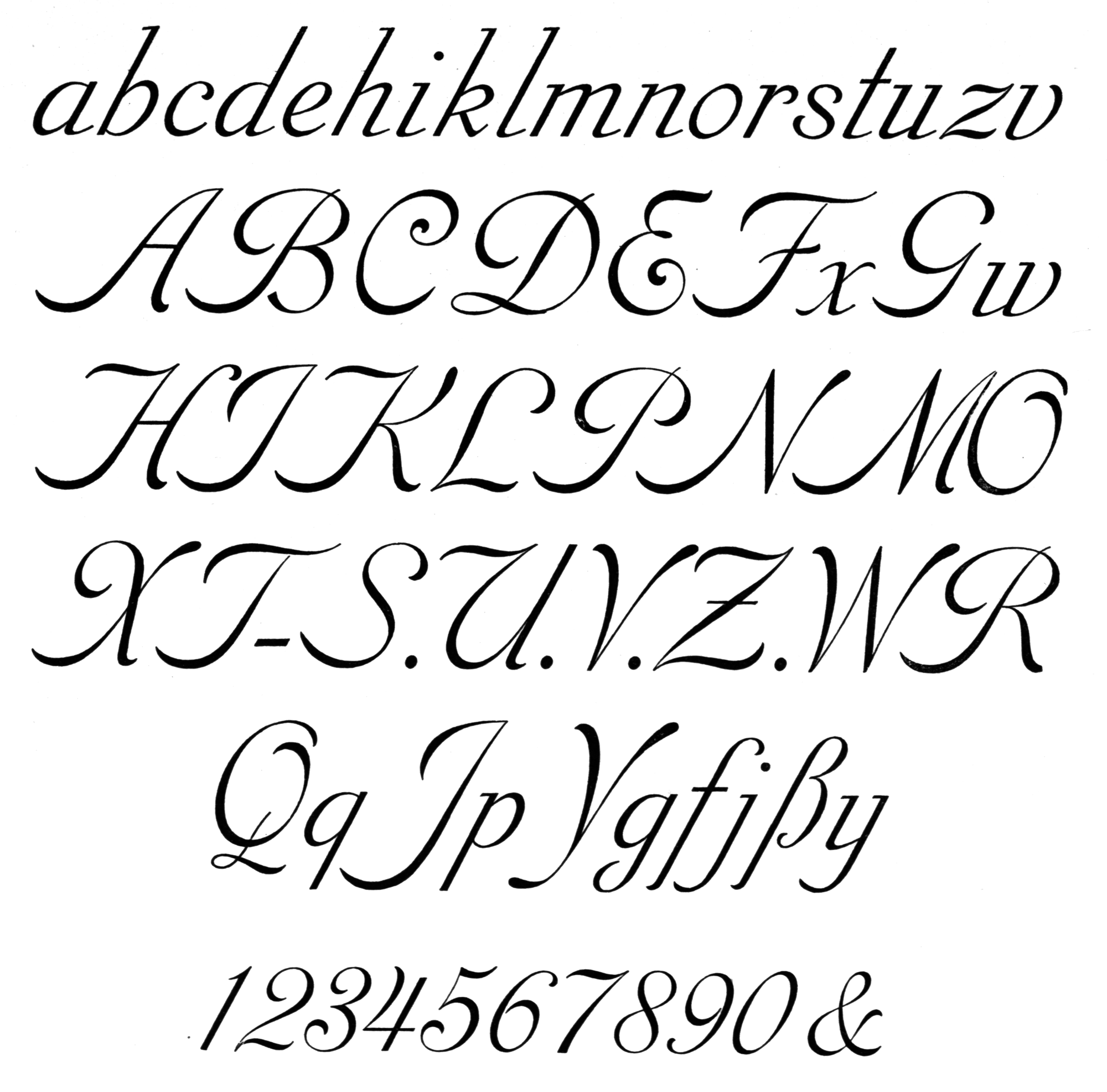
Font-Wiki: Kunstschrift Elfe
• 1904
• Antiqua Schreibschrift
Die (Kunstschrift) Elfe ist eine unverbundene Schreibschrift und erschien 1904 als Hausschnitt ohne Gestalterangabe bei der Gießerei Ludwig & Mayer in Frankfurt am Main »für Karten, Zirkulare und Akzidenzen«. Es waren eine magere und eine halbfette Garnitur verfügbar.